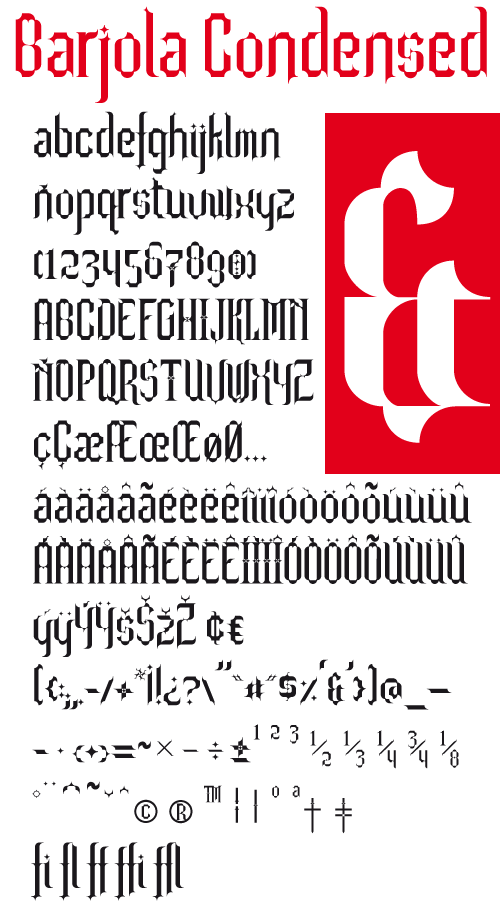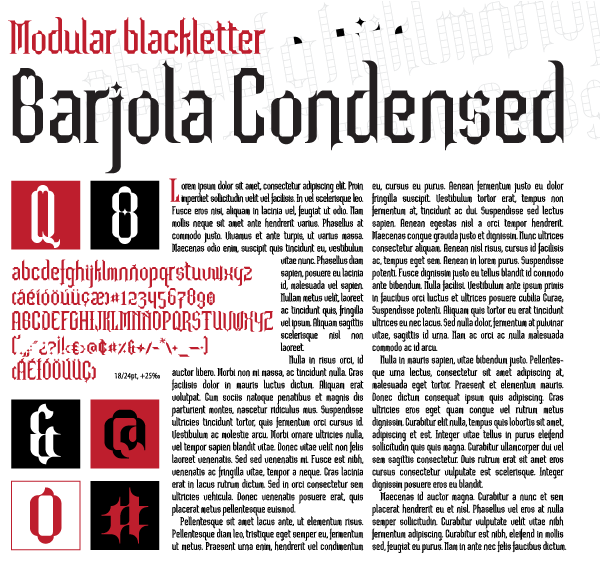
the ligatures fi fl ... ff they come off you
with great force !! Congratulations
the ligatures fi fl ... ff they come off you
with great force !! Congratulations